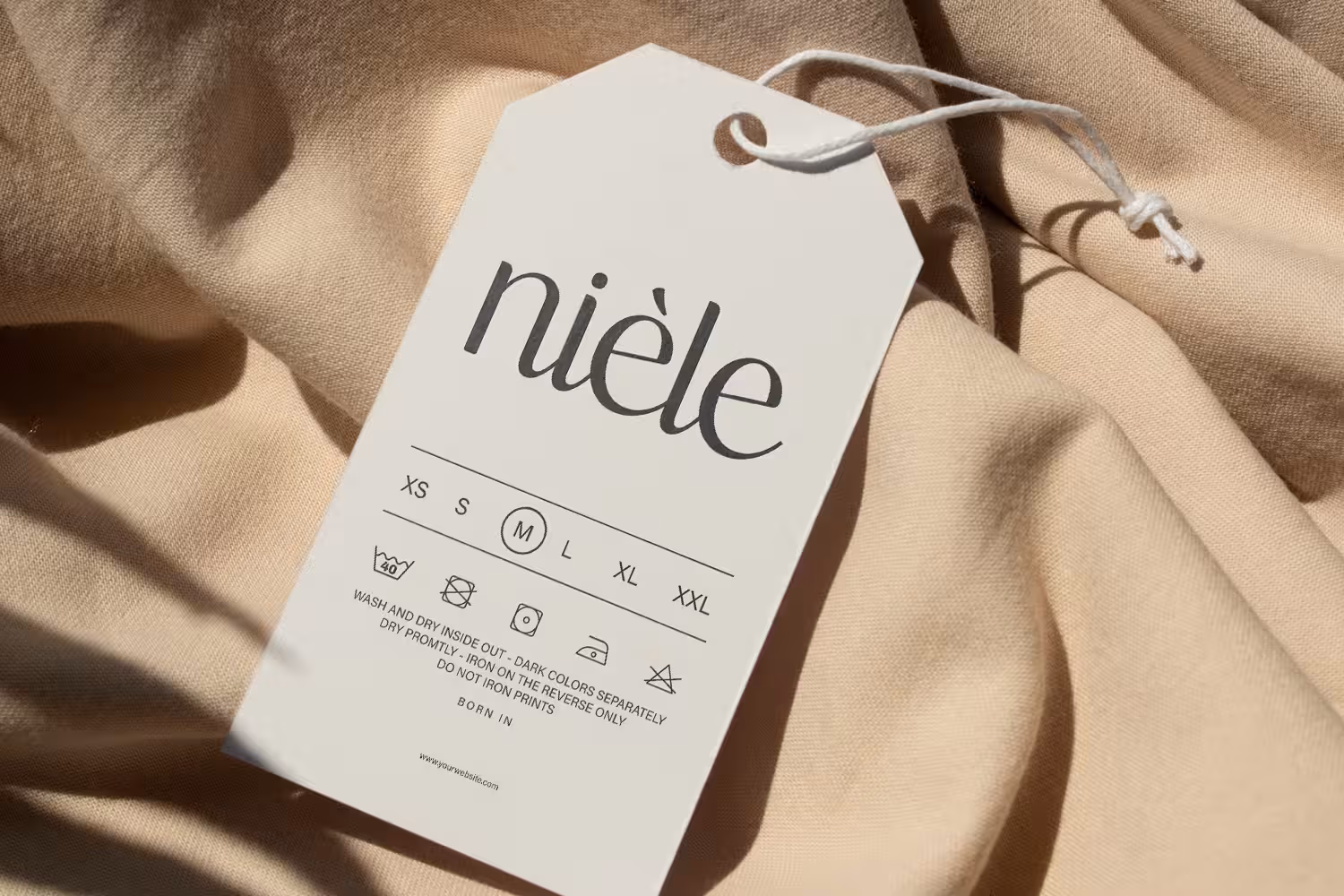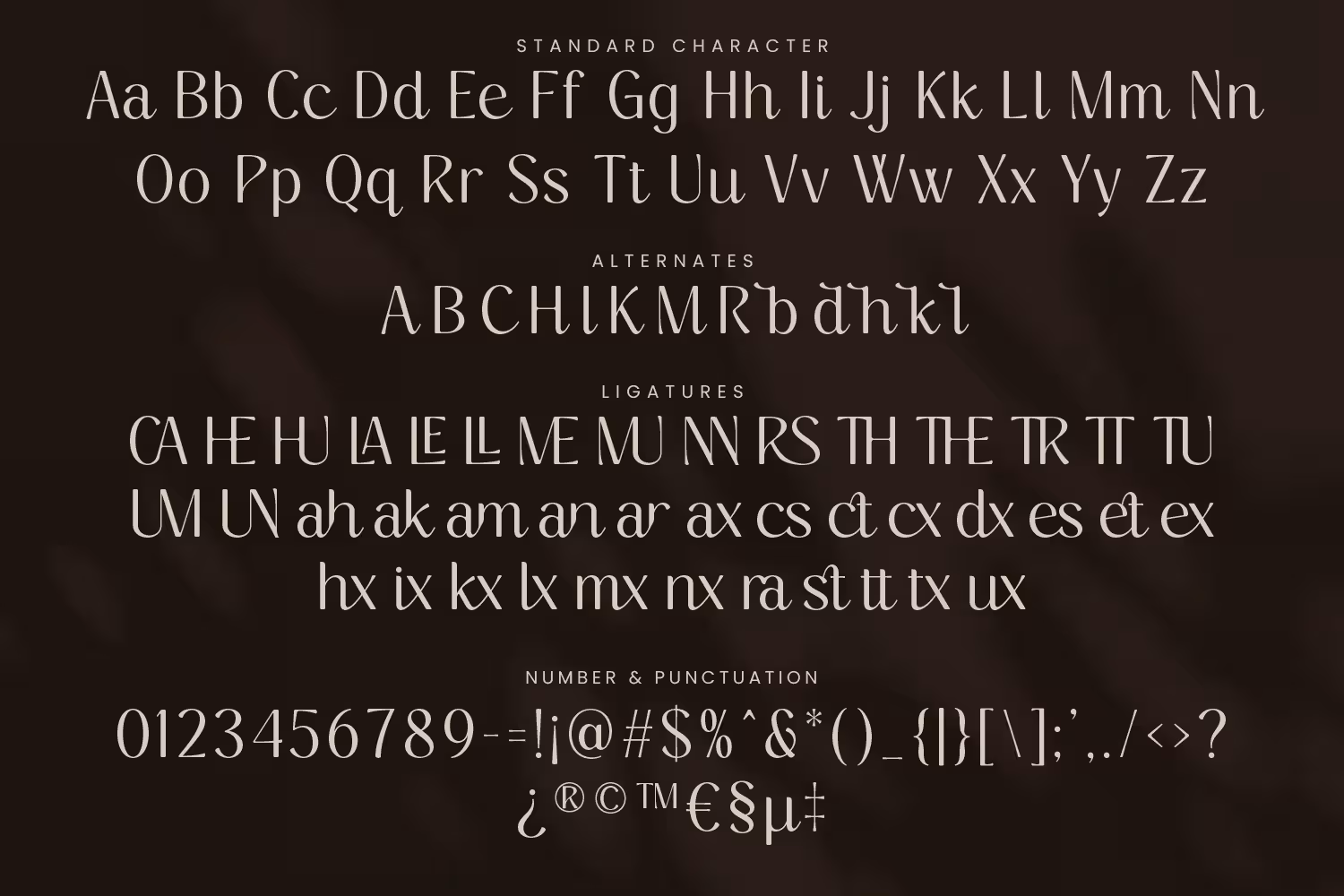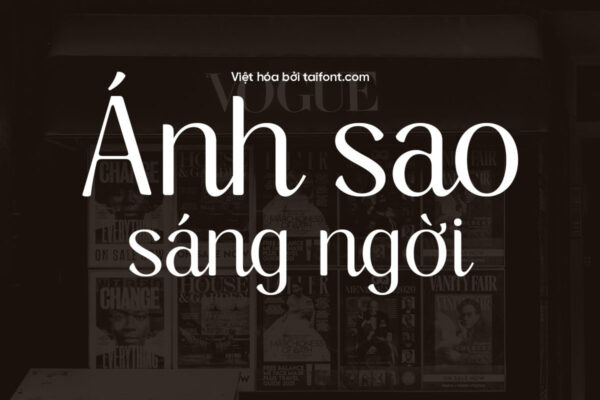
Giới thiệu về Font TF Bellamora Việt hóa
TF Bellamora Việt hóa là một font chữ có chân (serif) mang vẻ đẹp tinh tế và mềm mại nhờ các nét bo tròn duyên dáng. Sự kết hợp giữa sự cổ điển của serif và những đường cong uyển chuyển tạo nên một phong thái sang trọng, hiện đại nhưng vẫn rất thân thiện và quyến rũ.
Font này là lựa chọn lý tưởng cho các thiết kế đòi hỏi sự thanh lịch, nữ tính và cao cấp, đặc biệt trong các lĩnh vực:
- Mỹ phẩm: Hoàn hảo để sử dụng trên bao bì sản phẩm, catalogue, hoặc các chiến dịch quảng cáo, giúp khẳng định chất lượng và sự tinh tế của thương hiệu mỹ phẩm, làm nổi bật vẻ đẹp của sản phẩm.
- Thời trang: Lý tưởng cho các thương hiệu thời trang cao cấp, nhãn mác sản phẩm, lookbook, hoặc các ấn phẩm quảng bá bộ sưu tập. Font này giúp truyền tải sự thanh lịch, phong cách và nét mềm mại, quyến rũ của trang phục.
Với TF Bellamora Việt hóa, bạn có thể dễ dàng tạo ra những thiết kế không chỉ đẹp mắt mà còn truyền tải được thông điệp về sự sang trọng, tinh tế và vẻ đẹp đầy cuốn hút.
Font Việt hóa TF Bellamora